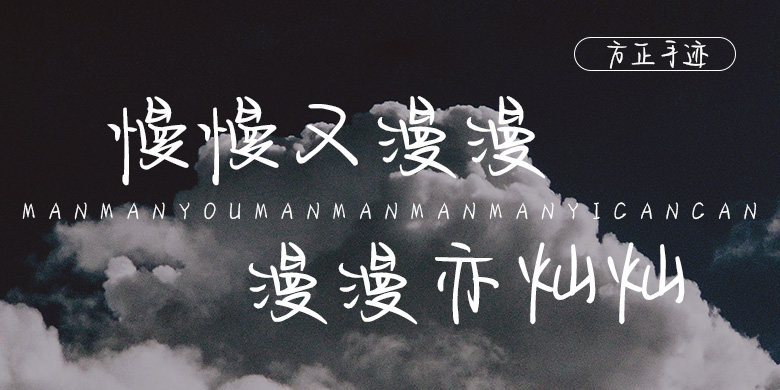
方正手迹-慢慢又漫漫漫漫亦灿灿
字体品牌: 方正手迹 设计师:宋昱东 字体分类:常规书写·硬笔 字体属性:精品字 字符集:简繁扩展(GBK) 发布时间: 2020
慢慢又漫漫漫漫亦灿灿是一款流行的青春风格手写字体,用笔简洁,主笔拉长,显的重心偏上,青春浪漫,而又不拘一格,风华正茂。适用于青少年类的书刊、品牌广告和产品包装设计,以及社交网络的个性化用字。